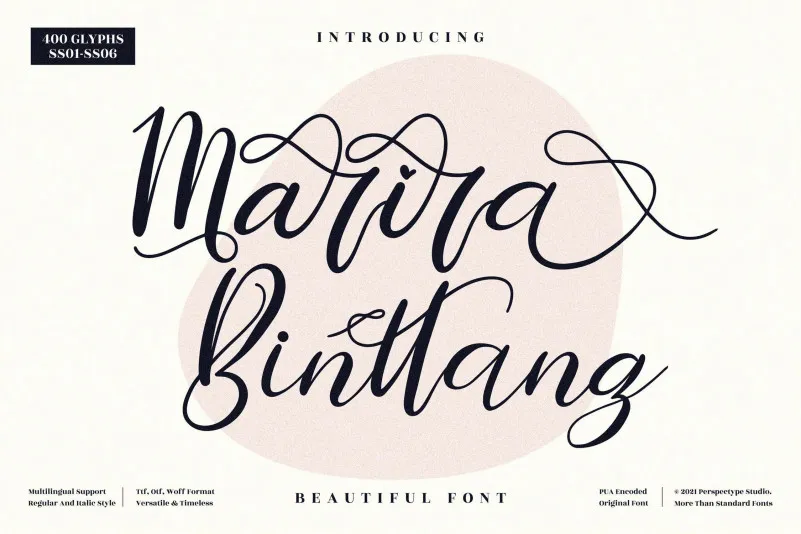
A fonte Marira Binttang é uma elegante tipografia de escrita manuscrita leve que transmite um encanto único e uma impressionante impacto visual. Especialmente adequada para projetos design desejáveis, ela adicionará um brilho sofisticado a qualquer projeto de design que você planeje criar. O fato de ser PUA encoded significa que você pode acessar facilmente todos os maravilhosos caracteres e ligaturas que este tipo tem. Esta fonte é perfeitamente adaptada para ambientes de design gráfico luxuoso, como editoriais pessoais, capas de livros de arte, cartões de aniversário personalizados ou até mesmo revistas fashion. A Marira Binttang não apenas impressiona pela sua beleza e elegância, mas também pela facilidade com que você pode integrá-la em seus projetos design digitais.